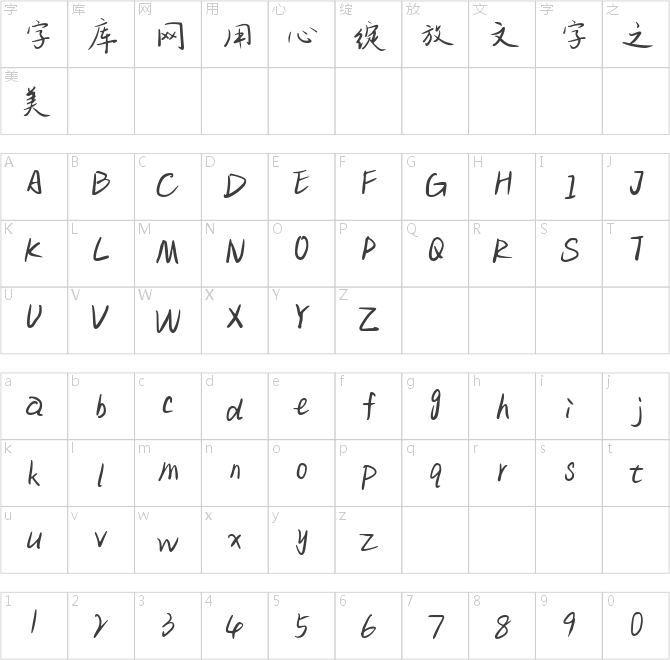
字體名稱: 沐浴風(fēng)雨中
沐浴風(fēng)雨中
沐浴風(fēng)雨中介紹
沐浴風(fēng)雨中字體字庫是一款讓人賞心悅目、百看不厭的中文字體,適合各類廣告和產(chǎn)品包裝設(shè)計應(yīng)用,字體大小8.22MB,格式為ttf字體,上傳用戶是三極字庫,作者/版權(quán)方為三極字庫